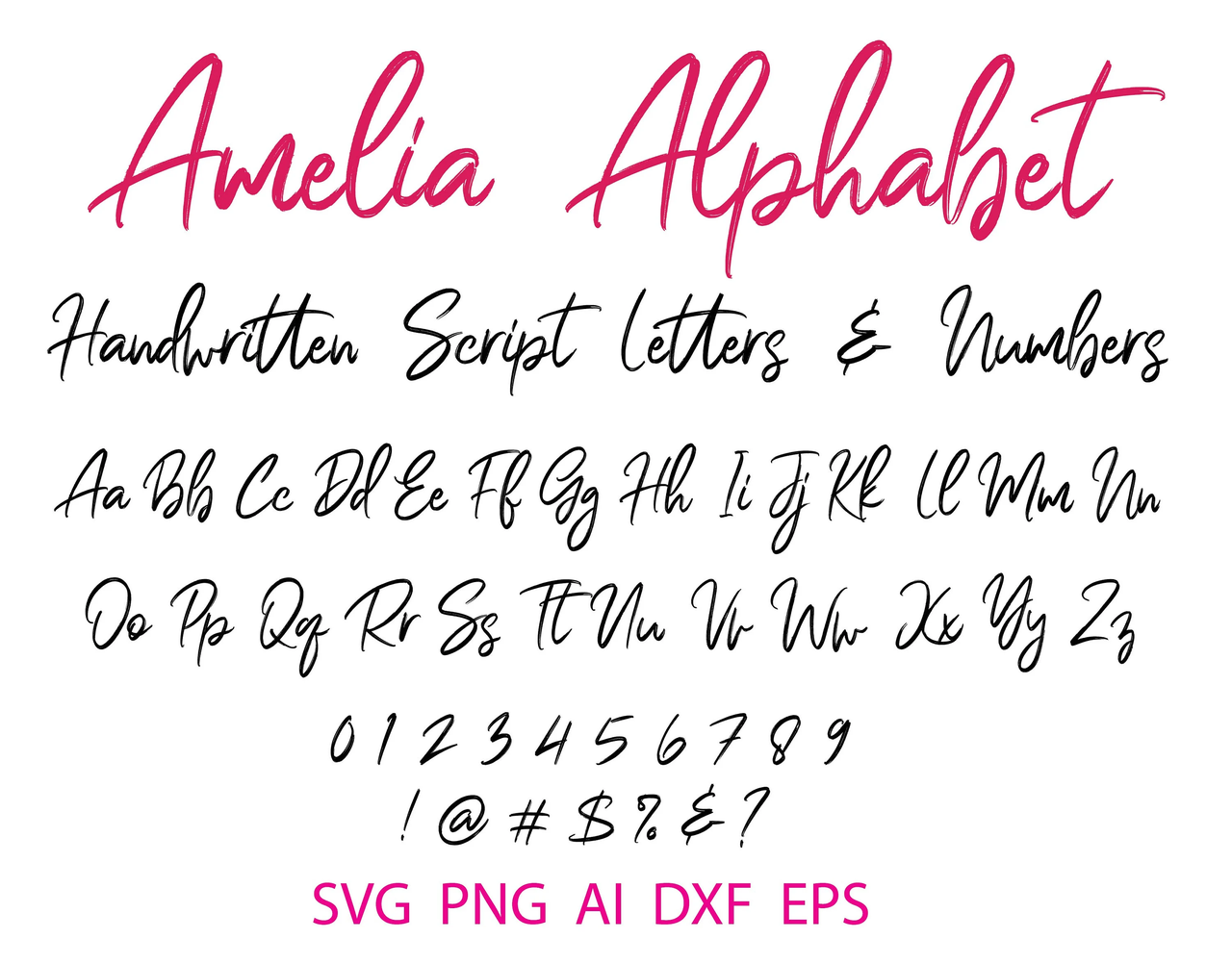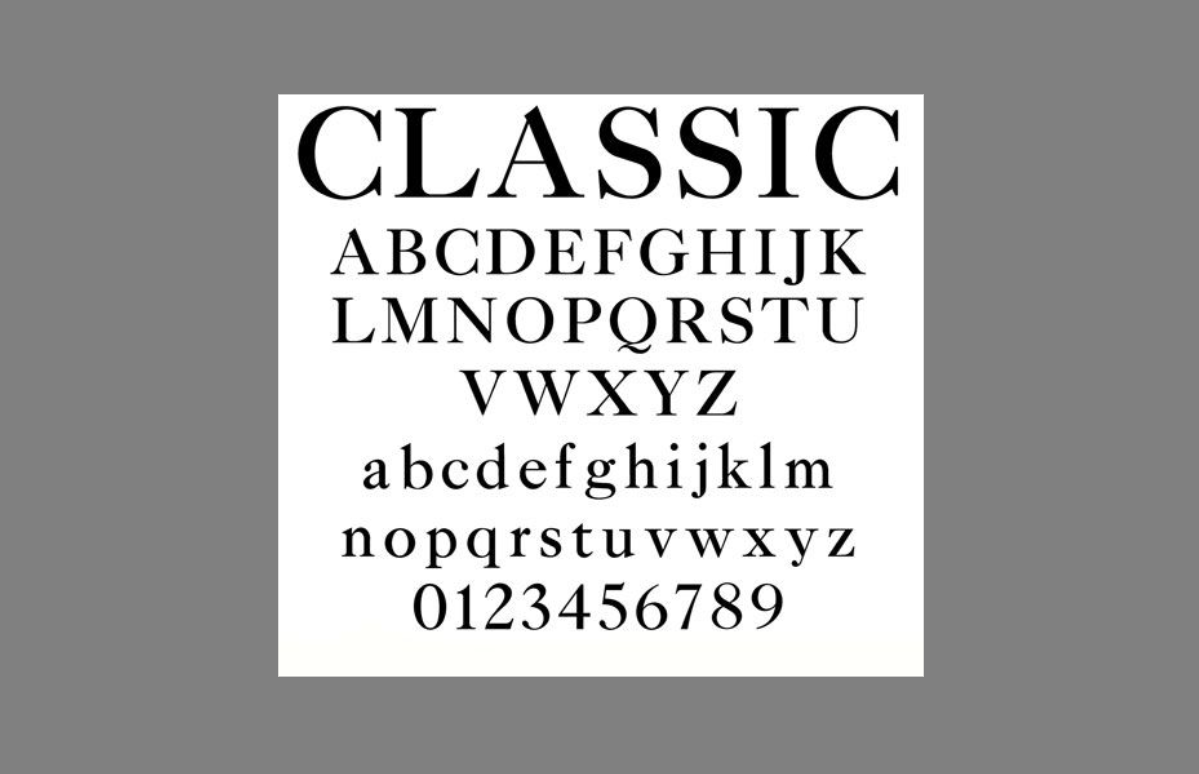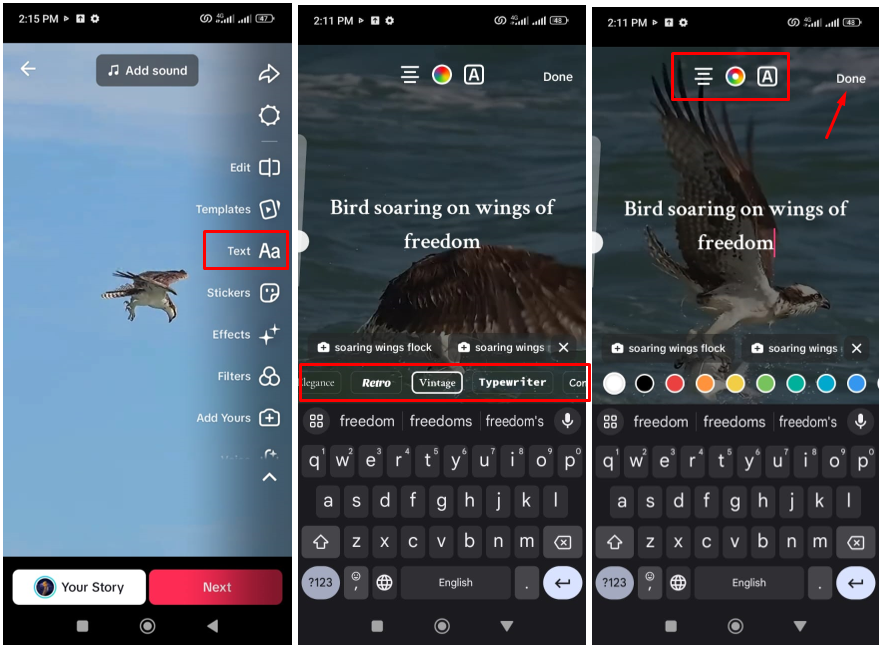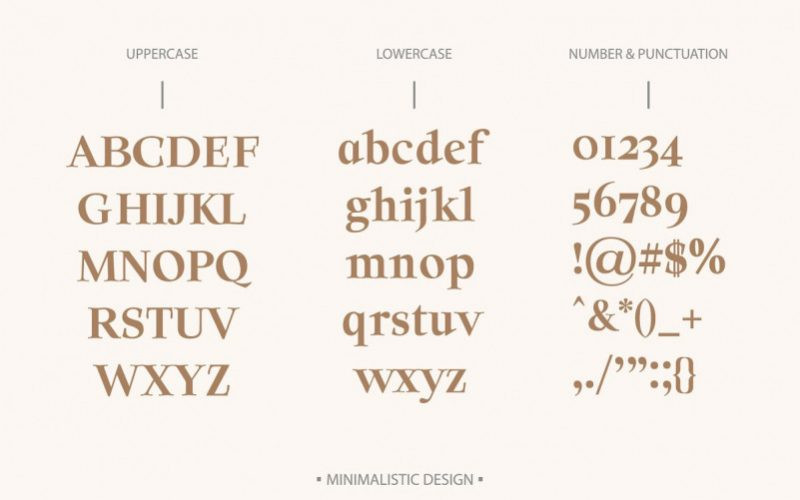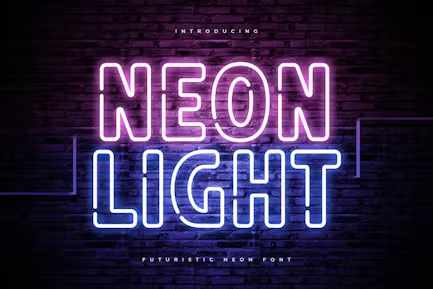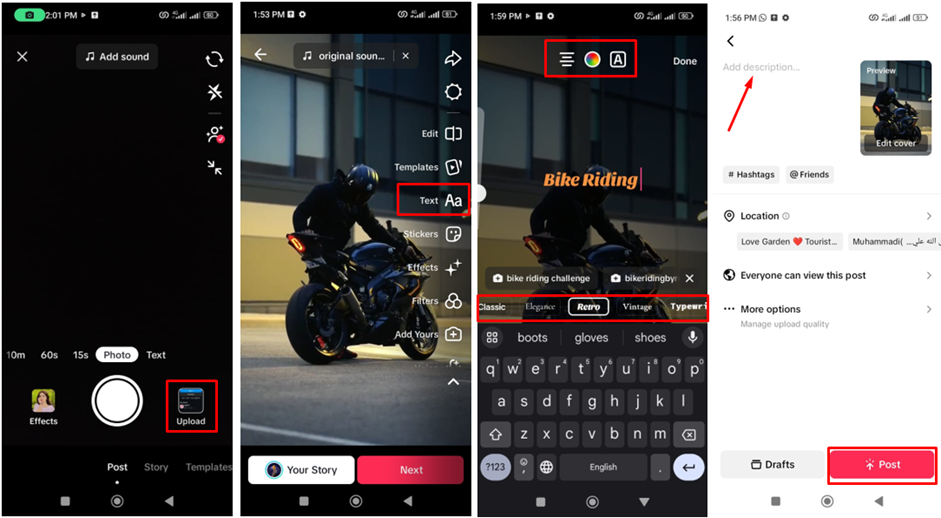
ユニークで魅力的な動画に最適なTikTokフォントスタイル
ユニークで創造的なTikTokフォントスタイルとアプリ内カスタマイズオプションを発見して、ビデオエンゲージメントを向上させましょう。TikTokビデオ用の究極のカスタムフォントジェネレータであるCapCutをご覧ください。
魅力的なTikTokビデオを作成するには、コンテンツだけでなく、プレゼンテーションも必要です。適切なフォントスタイルを使用すると、キャプションを目立たせ、ビデオに個性を加え、視聴者を引き付けることができます。
この記事では、あなたのビデオを強化し、他の人と区別することができる最高のTikTokフォントスタイルを探ります。トレンディで遊び心のあるフォントから洗練されたプロフェッショナルなオプションまで、あらゆるコンテンツに最適なスタイルを選択する方法を説明します。
TikTokはどのフォントを使用していますか
TikTokは、コンテンツを際立たせ、メッセージを効果的に伝えるためのさまざまなフォントを提供しています。各フォントのユニークな特性を理解することで、ビデオに適したフォントを選択することができます。このパートでは、TikTokフォントについて知っておく必要があるすべてを学びます。
クラシック
Classicは、TikTokの初期の日々やProxima Nova書体を思い起こさせる、ノスタルジアを感じさせるシンプルでクリーンなフォントです。本文に最適で、メインコンテンツから注意をそらすことはありません。このフォントは、明確さが重要なハウツー動画やコンテンツに最適です。
クラシックフォントを使用する:
• ハウツー動画。
• チュートリアル。
• 情報コンテンツ。
• 明確さが重要なキャプション。
クラシックフォントを使用しない:
• より表現力豊かなフォントが必要な創造的または芸術的なビデオ。
• よりダイナミックなフォントが良いかもしれない、高エネルギーまたはトレンディなコンテンツ。
• テキストを主要なビジュアル要素として目立たせたいビデオ。
Classic is a simple and clean font for TikTok
タイプライター
TikTokのタイプライターフォントはビンテージ感があり、レトロやノスタルジックなコンテンツに最適です。それは、オールドスクールのタイプライターや1950年代のノワールの雰囲気を思い起こさせます。このフォントは、長い段落が読みにくくなるため、短くインパクトのあるテキストに最適です。
タイプライターフォントを使用する:
• レトロまたはビンテージテーマのビデオ。
• 短く、インパクトのあるメッセージ。
• ノスタルジックなタッチの引用やキャプション。
Typewriterフォントを使用しない:
• 長い段落や詳細な説明。
• スピード感のあるまたはモダンなコンテンツ。
• 早く読む必要のあるテキスト。
Typewriter
手書き
手書きは、TikTok用の女性的でコテージコアなスタイリッシュなフォントで、美容やファッションに関するコンテンツに最適です。個人的なタッチを加え、見出しや短いフレーズに最適です。視覚的に魅力的ですが、長いテキストブロックでは読みにくい場合があります。
手書きフォントを使用する:
• 美容やファッションのコンテンツ。
• 個人的なメモや短いメッセージ。
• タイトルと見出し
手書きフォントを使用しないでください:
• 長いテキストブロックや詳細な説明。
• 迅速な読みやすさが必要なコンテンツ。
• 技術的または情報的なビデオ。
Handwriting is a feminine, cottage-core stylish font for TikTok
ネオン
ネオンは、TikTokビデオ用の明るく幾何学的で目を引くフォントスタイルであり、あなたのコンテンツにポップアートやベガスのような雰囲気を与えます。目立つように設計されており、短く影響力のあるメッセージに最適です。長いテキストには使用しないでください。数語で強いステートメントを作ることができます。
ネオンフォントを使用する:
• 短く、注目を集めるメッセージ。
• キーポイントを強調する。
• エネルギッシュで活気のあるコンテンツ。
Neonフォントを使用しないでください:
• 長い段落や詳細な情報。
• 微妙さが必要なコンテンツ。
• プロフェッショナルまたはフォーマルなビデオ。
Neon is a bright font style for TikTok videos
セリフ
セリフは、エレガントで洗練された感覚を加えるTikTokの美的ビデオ用の伝統的なセリフフォントです。本文とタイトルの両方に使用できるほど多目的です。小文字のセリフは長いテキストに適しており、すべての大文字は見出しに使用してクラシックなタッチを加えることができます。
セリフフォントを使用する:
• 美しいまたはエレガントなコンテンツ。
• 長いテキストまたは詳細な説明。
• クラシックな雰囲気のタイトルと見出し。
セリフフォントを使用しない:
• 現代的またはミニマリストの外観が必要なコンテンツ。
• スピーディーで高エネルギーな動画。
• 非公式またはカジュアルなコンテンツ
Serif is a traditional serif font for TikTok aesthetic videos
究極のTikTokフォントジェネレーター:CapCutデスクトップビデオエディター
CapCutデスクトップビデオエディターは、あなたの究極のTikTokフォントジェネレーターであり、ビデオを強化するための創造的なツールの範囲を提供します。AI生成機能により、必要に応じてスタイリッシュなテキストを簡単に生成できます。直感的なインターフェースと多様な機能により、魅力的なタイポグラフィとprofessional-quality編集機能でビデオを際立たせたいクリエイターにとって必須のアイテムです。
Interface of the CapCut desktop video editor– the best tool for generating TikTok text fonts
主な特徴
• AIを使ってカスタムTikTokフォントを作成する
AIを使って簡単にカスタムTikTokテキストフォントを作成し、ビデオの視覚的な魅力と独自性を高めます。
1. TikTok用の無料フォントジェネレーターはありますか?
TikTokにはいくつかの無料のオンラインフォントジェネレータがありますが、CapCutデスクトップビデオエディタを使用すると、より効率的で高度なエクスペリエンスを提供できます。CapCutを使用すると、エディタ内でAIを使用して簡単にフォントを生成できます。その高度な機能により、ビデオコンテンツを強化するprofessional-qualityテキストスタイルを作成できます。
3
1. TikTok用のスタイリッシュなフォントを作成する方法は?
美的なコンテンツのためのスタイリッシュなTikTokフォントを作成することは、CapCutデスクトップビデオエディターで簡単です。フォントのアイデアを提供するだけで、CapCutの高度なツールがAIを使用してフォントを生成します。さまざまなフォントスタイルから選択したり、体格、色、効果を調整したり、テキストをアニメーション化してコンテンツにダイナミックな要素を追加することもできます。